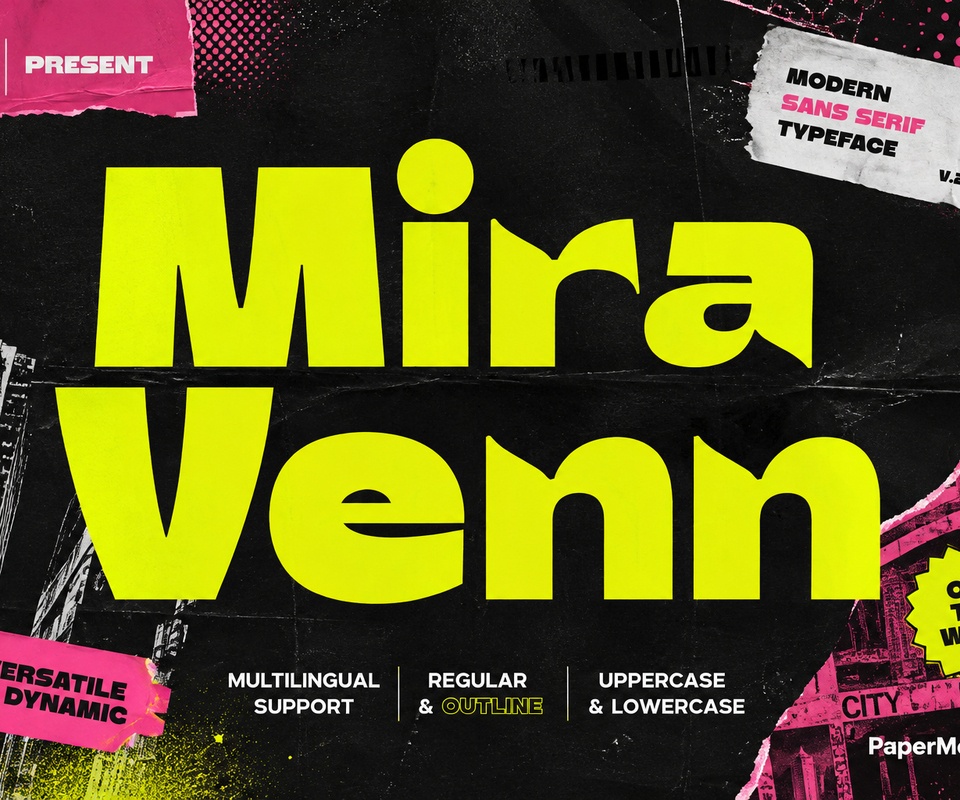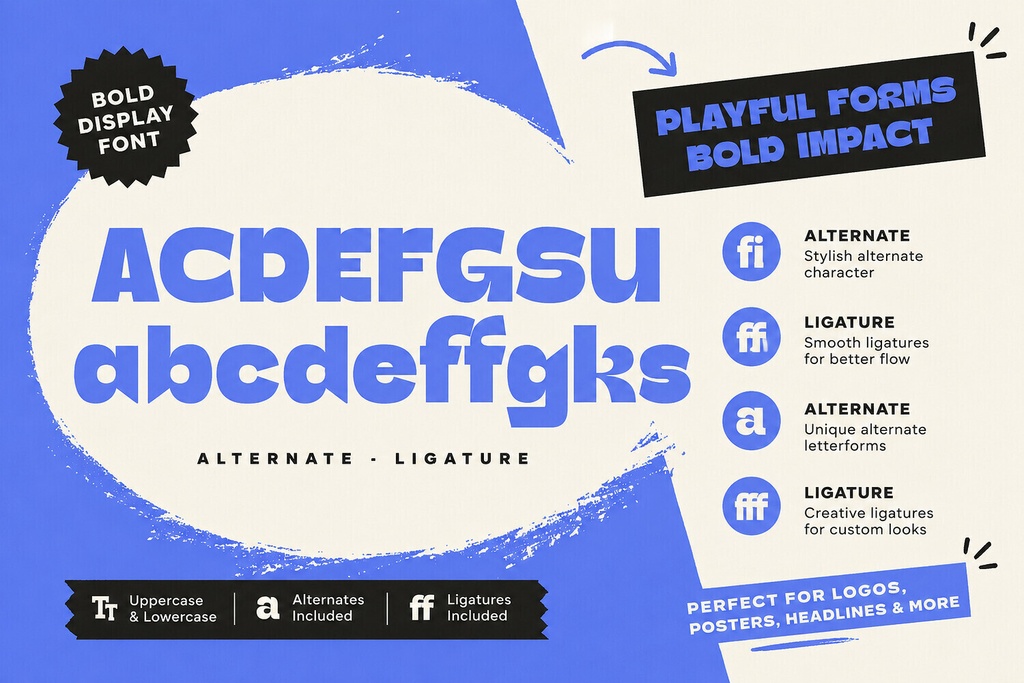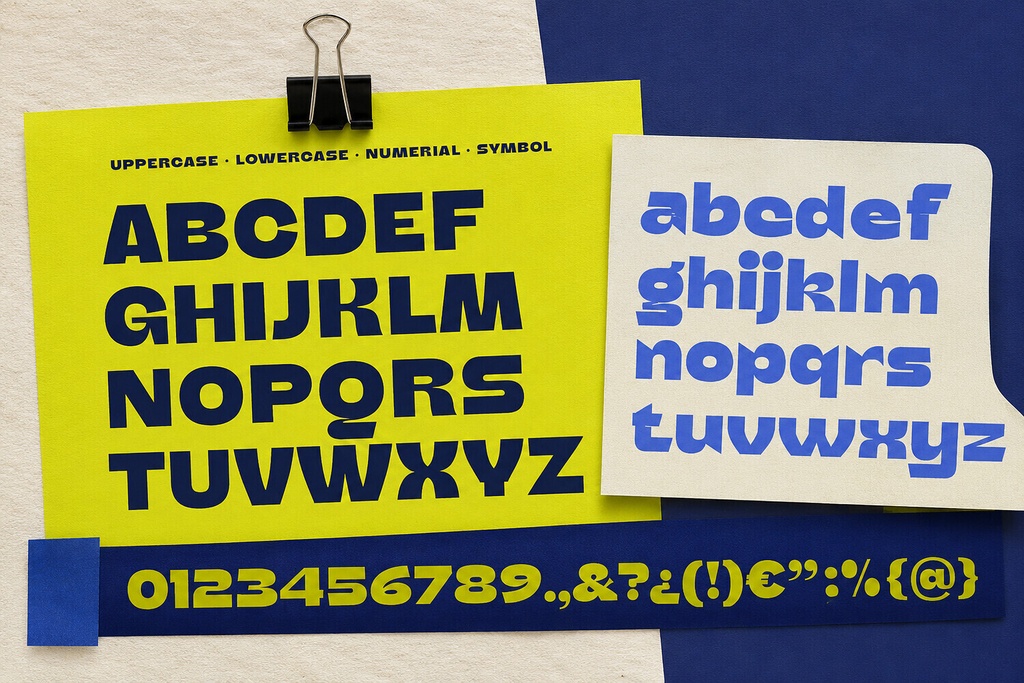
Mira Venn - 太字で遊び心のあるサンセリフディスプレイフォント
**Mira Venn**は、太めでモダンなサンセリフのディスプレイフォントです。ファンキーで遊び心のある個性、力強いフォルム、そして柔らかな角を特徴としています。見出し、ロゴ、ブランド用のレタリングに親しみやすい印象を与えながら、情報量の多いレイアウトの中でもしっかりと存在感を発揮します。 ### これはどんなフォント? Mira Vennは、ディスプレイタイポグラフィーや表現力豊かな日常のデザイン制作のために作られた、**Regular 1スタイル**のフォントです。丸みのある太めのサンセリフ形状により、クリーンでモダンなフォントに、より温かみや動き、個性を加えたい場合に特に効果的です。 収録フォントには**262種類のグリフ**が含まれており、大文字・小文字、数字、記号、句読点、アクセント付き文字などに対応しています。 ### 主な特徴 Mira Vennには、より個性的なレタリングを作るための**40種類のオルタネート文字とリガチャ**が収録されています。 オルタネート文字を使用することで、繰り返し登場する文字に変化を加えたり、ワードマークのリズムを調整したり、短い見出しをより個性的なデザインに仕上げたりできます。 リガチャでは、対応する文字の組み合わせに対して、つながりのあるデザイン表現を使用できます。これらのOpenType機能は、標準的なOpenTypeコントロールに対応したソフトウェアで利用できます。一方、基本的なフォント対応ソフトでは、通常のフォントとして簡単にインストールして使用できます。 ### 用途 この遊び心のあるサンセリフフォントは、以下のようなデザインにおすすめです。 * ロゴ * モダンなブランディング * 大胆なワードマーク * ポスター * パッケージデザイン * 商品ラベル * エディトリアル用見出し * キャンペーンタイトル * SNSグラフィック * アパレル用レタリング * プレゼンテーション * Webサイトのディスプレイテキスト 太めのディスプレイフォントスタイルは、クリエイティブ系ビジネス、ライフスタイル商品、食品・飲料ブランド、若者向けキャンペーン、イベントグラフィックなど、柔らかさを持ちながら大胆なブランディングを必要とするプロジェクトに適しています。 親しみやすい丸みのある文字デザインにより、短いフレーズにもインパクトを保ちながら、より approachable(親しみやすい)な印象を与えることができます。 ### 言語サポート Mira Vennは、以下の言語に対応しています。 **デンマーク語、英語、エストニア語、フィリピン語、フィンランド語、フランス語、フリウリ語、ガリシア語、ドイツ語、グシイ語、インドネシア語、アイルランド語、イタリア語、ルクセンブルク語、ノルウェー語(ブークモール)、ノルウェー語(ニーノシュク)、ニャンコレ語、オロモ語、ポルトガル語、ロマンシュ語、ロンボ語、スペイン語、スウェーデン語、スイスドイツ語、ウズベク語(ラテン文字)** この多言語対応により、国際的なブランディング、パッケージ、エディトリアルグラフィック、キャンペーン、より幅広いラテン文字圏の言語を必要とするデジタルコンテンツなどにも便利です。 ### 互換性とファイル形式 パッケージには以下のファイル形式が含まれています。 * **OTF** * **TTF** * **WOFF2** Canva、基本的なデザインソフト、標準フォントに対応したWebアプリでは、OTFまたはTTFファイルをインストールして使用できます。 WOFFおよびWOFF2ファイルは、対応するWebフォント環境で使用できます。 オルタネート文字やリガチャのサポートは使用するアプリケーションによって異なりますが、通常のフォントのインストールや基本的な使用に特別なデザインソフトは必要ありません。 ### ライセンス Cubebrush Commercialライセンスでは、Cubebrushのライセンス規約に従うことを条件として、クレジット表記なしで商用デザインに使用できます。 フォントファイルを単独の商品として再配布したり、この書体を自分で制作したものとして主張したりすることは禁止されています。 個人利用および非商用プロジェクトの場合は、**Basicライセンス**を選択してください。 次の見出しに、より柔らかく遊び心のあるエネルギーを加えてみませんか? **Mira Vennで、あなたのデザインに大胆さと親しみやすさをプラスしましょう。**